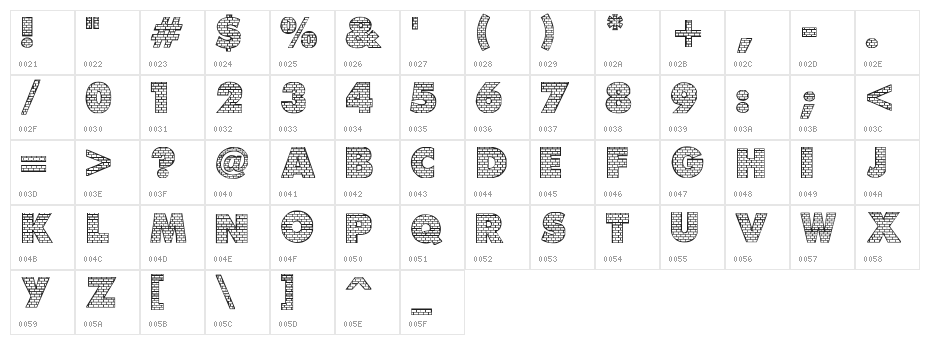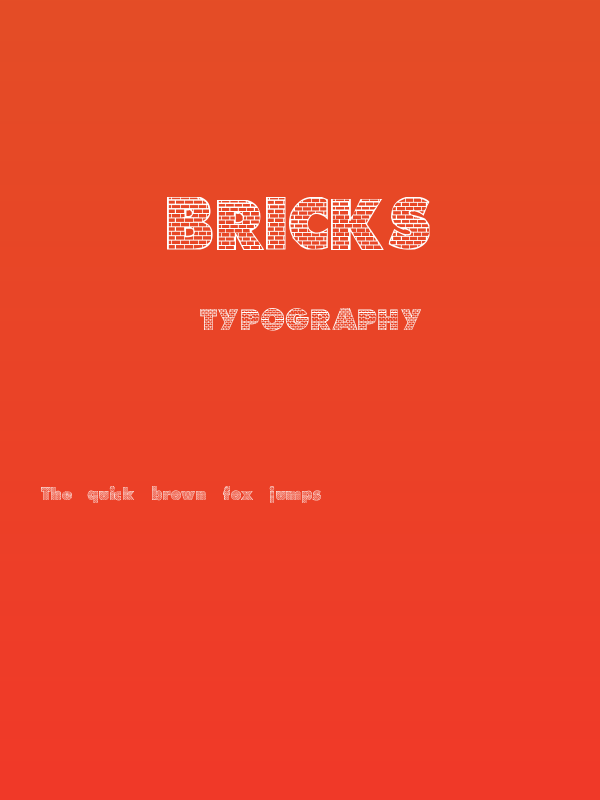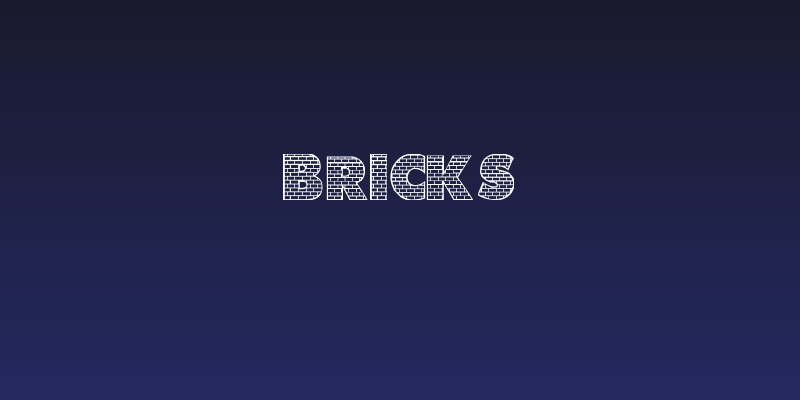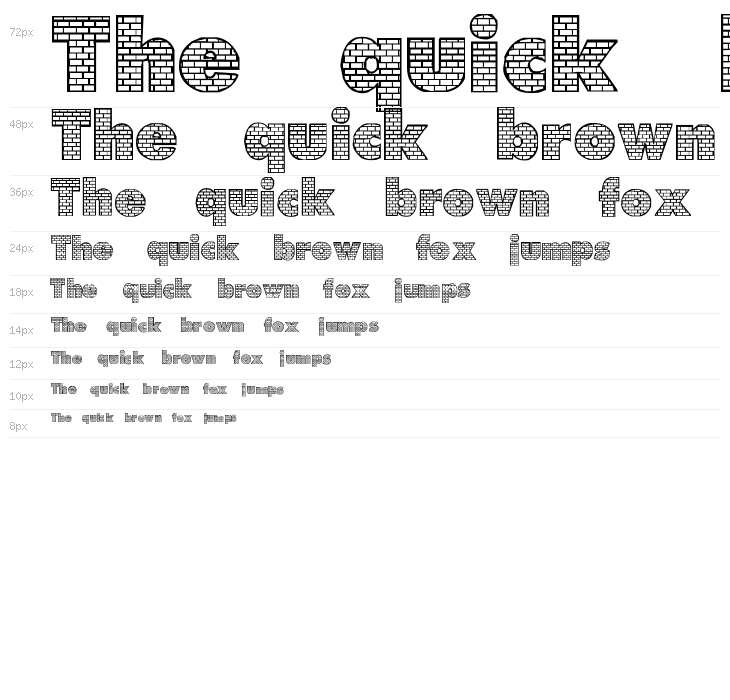
Bricks Font
| Progetti proposti | Ideal for posters, children's book covers, themed event invitations, or any project requiring a playful and architectural aesthetic. |